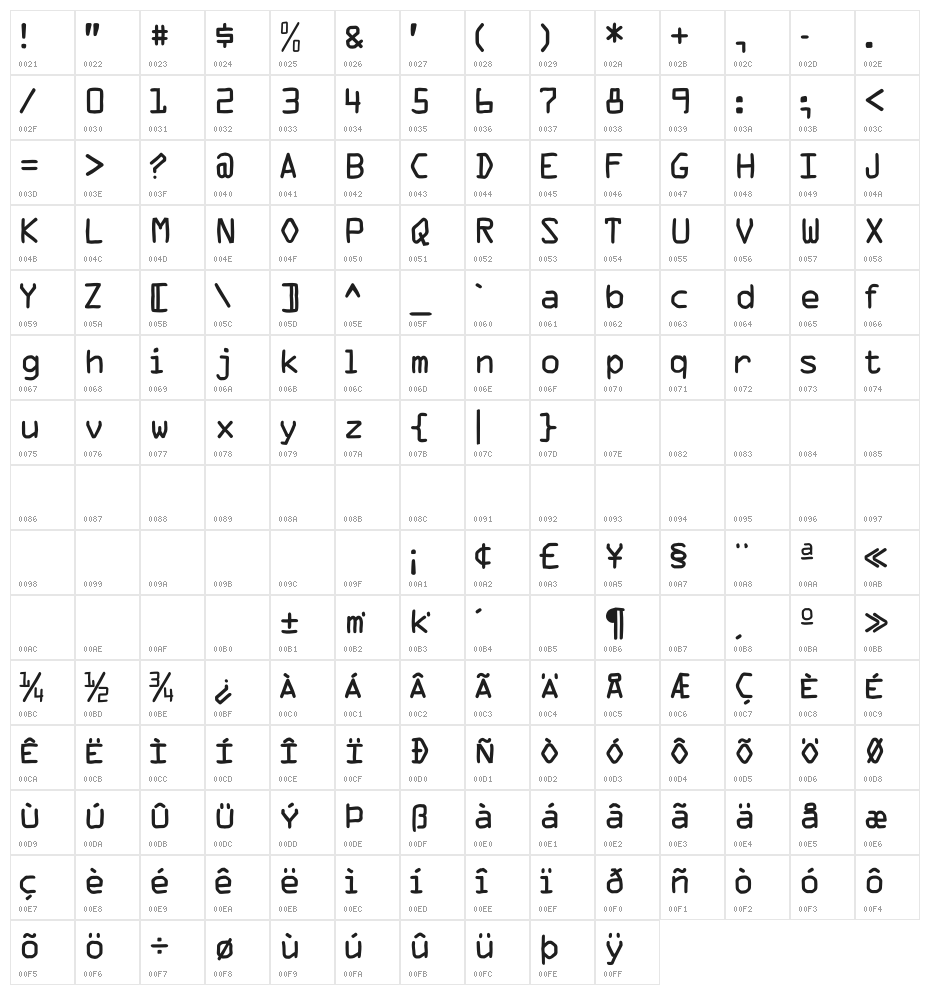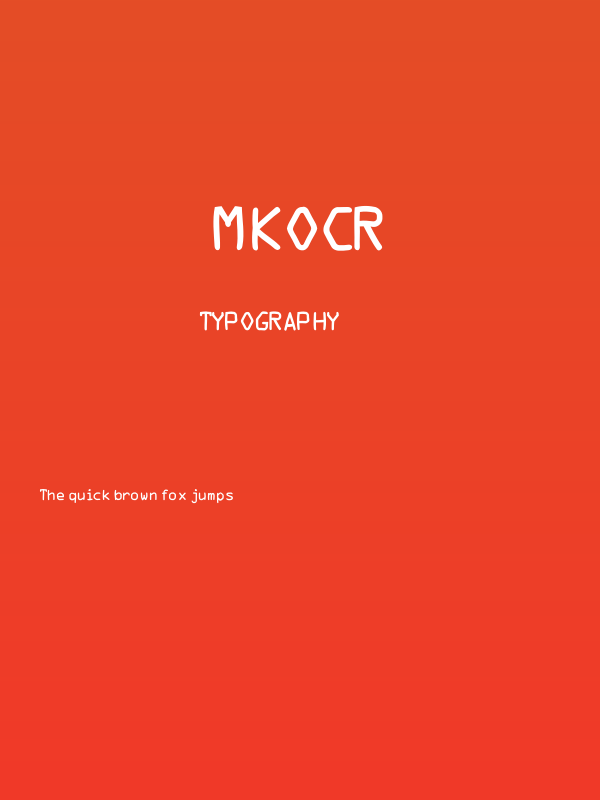
MKOCR Font
| Общий стиль | Playful |
| Область применения | Headlines, Logos, Informal Text |
| Рекомендуемые проекты | Ideal for children's books, playful branding, greeting cards, and informal invitations. |